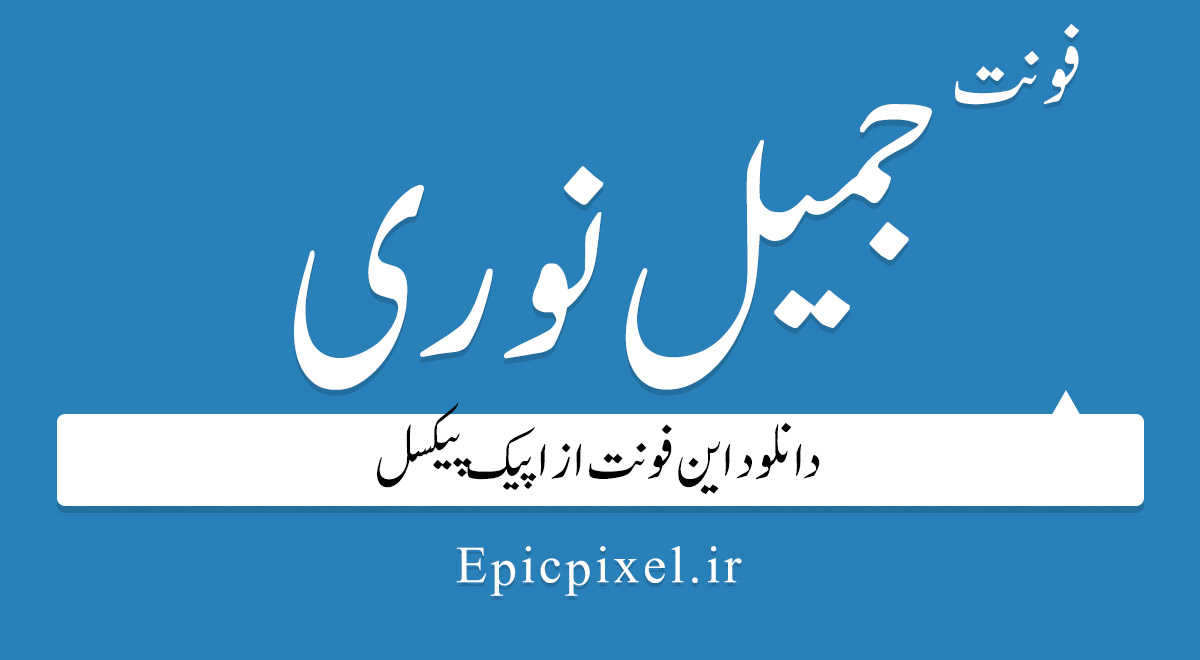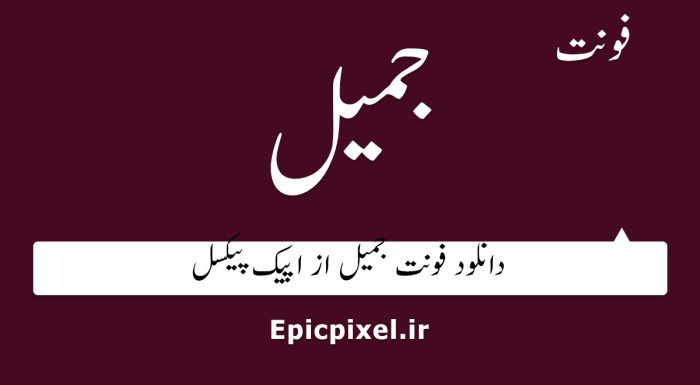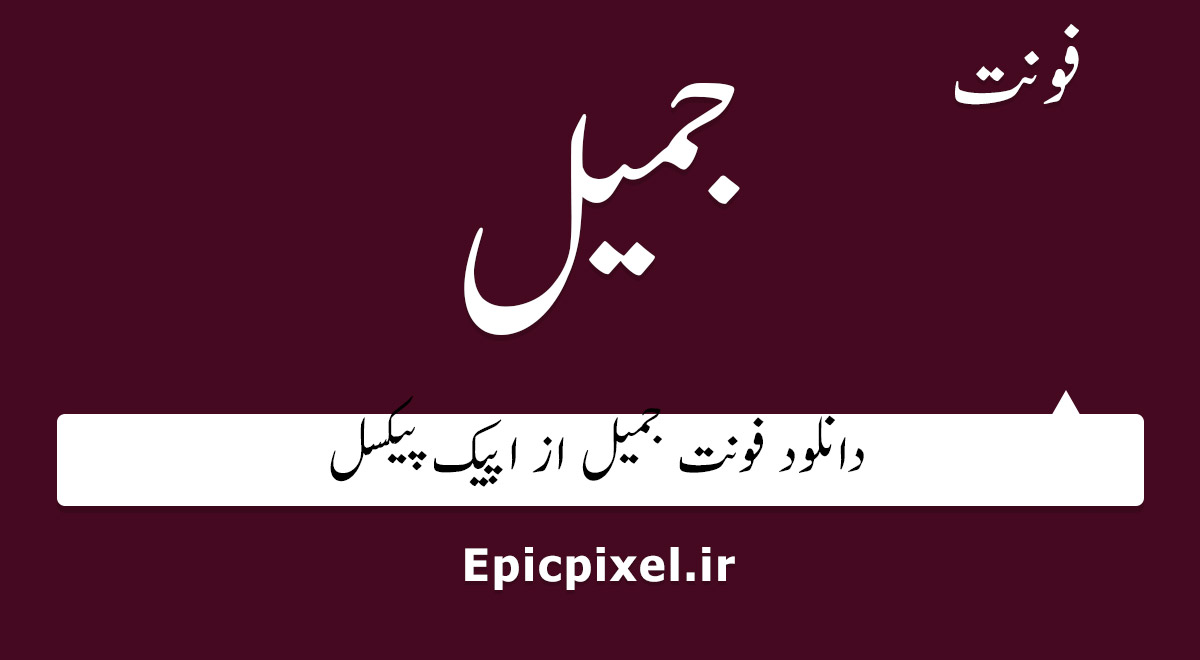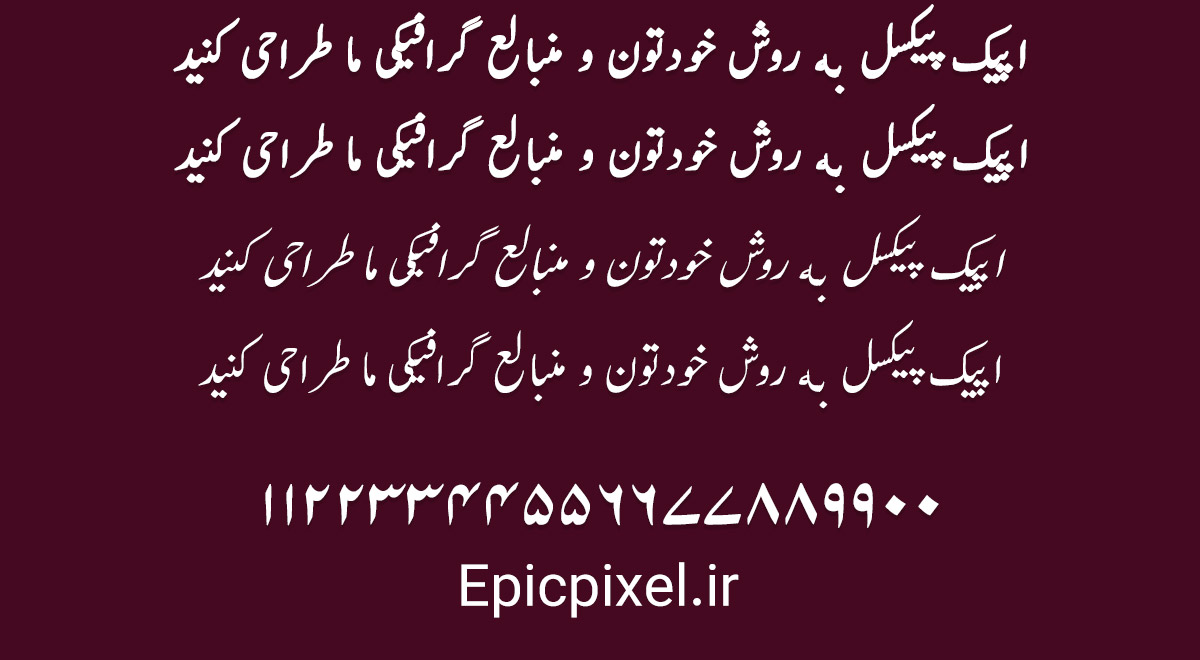
4 فونت جمیل فارسی Jameel
مجموعه کامل ۴ فونت جمیل فارسی، یک گنجینه رایگان از قلم های زیبا در سبک نستعلیق و خوشنویسی است. این مجموعه با فونت جمیل نوری نستعلیق کلاسیک، فونت جمیل نوری کشیده با قابلیت کشیدگی منحصربه فرد، و دو قلم جمیل خوش خطی استاندارد و L، تنوع بی نظیری را در اختیار طراحان قرار می دهد. این فونت ها که در ابتدا به عشق دوستداران زبان اردو منتشر شدند، ابزاری پرکاربرد و رایگان برای خلق تایپوگرافی های هنری و طرح های گرافیکی زیبا در زبان فارسی هستند و زیبایی خط نستعلیق را به سادگی در محیط دیجیتال فراهم می کنند.
مجموعه کامل ۴ فونت جمیل فارسی، یک پکیج ارزشمند و رایگان برای تمام علاقه مندان به خوشنویسی و استفاده از خط نستعلیق در طراحی های دیجیتال است. این مجموعه شامل چهار قلم اصلی است که هر یک ویژگی های متمایز خود را دارند و با نام “جمیل” شناخته می شوند: فونت جمیل نوری نستعلیق، فونت جمیل نوری کشیده (Jameel Noori Kasheeda)، فونت جمیل خوش خطی (Jameel Khush Khati) و فونت جمیل خوش خطی ال (Jameel Khush Khati L).
این فونت ها در مجموع، طیف متنوعی از سبک های نزدیک به نستعلیق و خوشنویسی را پوشش می دهند. فونت جمیل نوری نستعلیق نسخه استاندارد و شناخته شده این خانواده است که برای استفاده عمومی در متون و عناوین مناسب است. فونت جمیل نوری کشیده ویژگی برجسته قابلیت “کشیدگی” را ارائه می دهد که امکان طراحی خطوط نستعلیق با کشیدگی های زیبا و منحصربه فرد را فراهم می کند و به عنوان تنها و اولین فونت کشیده در سبک نوری نستعلیق شناخته می شود. دو قلم جمیل خوش خطی و جمیل خوش خطی ال نیز سبک متفاوتی از خوشنویسی و نستعلیق را ارائه می دهند که ممکن است در برخی جزئیات یا ضخامت خط با فونت های نوری متفاوت باشند و گزینه های بیشتری را برای انتخاب در اختیار طراح قرار می دهند.
دانلودنکته مهم در خصوص این مجموعه این است که تمامی فونت ها بصورت کاملاً رایگان عرضه شده اند. آن ها در ابتدا به عشق تمامی دوستداران زبان اردو توسط طراحانی که نامشان در برخی موارد مشخص نیست (مانند طراح فونت های جمیل نوری) منتشر شدند. با این حال، به دلیل زیبایی و کیفیت بالا، به سرعت در میان کاربران فارسی زبان نیز محبوبیت پیدا کرده و به ابزاری پرکاربرد برای تایپ مستقیم متون فارسی با خط نستعلیق تبدیل شده اند. داشتن تمام این ۴ قلم در یک مجموعه، انعطاف پذیری بالایی برای طراحان در انتخاب بهترین سبک و وزن برای پروژه خود ایجاد می کند.
کاربردهای مجموعه فونت های جمیل در طراحی
مجموعه کامل ۴ فونت جمیل فارسی، ابزاری قدرتمند برای خلق آثاری با حس و حال خوشنویسی و نستعلیق در انواع طرح های گرافیکی است. این فونت ها برای تایپوگرافی هنری، به خصوص در زبان های فارسی و اردو، کاربرد فراوان دارند.
از قلم های این مجموعه می توان در عناوین اصلی پروژه های چاپی و دیجیتال، جلد کتاب و مجله، پوسترها، بروشورها و کارت های دعوت استفاده کرد. آن ها برای طراحی لوگو و لوگوتایپ (به ویژه با استفاده از نسخه کشیده)، نقل قول ها، جملات قصار و متون ادبی بسیار مناسب هستند. استفاده از آن ها در عکس نوشته ها و پست ها و استوری های شبکه های اجتماعی به محتوا زیبایی بصری خاصی می بخشد. همچنین می توانند در وبسایت ها برای بخش های خاصی مانند هدر، عناوین مقالات یا نقل قول ها به کار روند. این مجموعه با ارائه چند سبک مختلف نستعلیق/خوشنویسی، به طراح اجازه می دهد تا بهترین قلم را متناسب با حس و حال دقیق پروژه خود انتخاب کند.